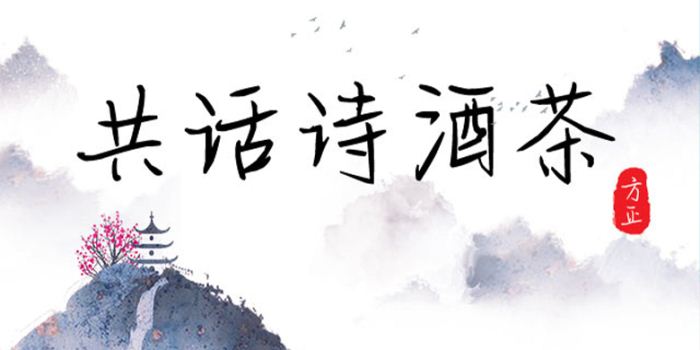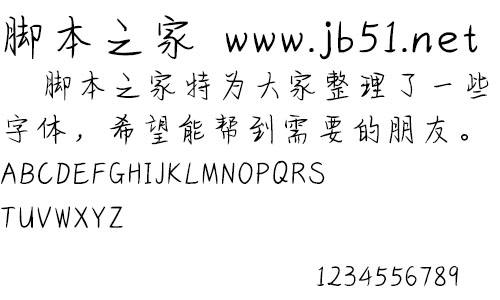
方正手跡-共話詩(shī)酒茶由方正字庫(kù)劉殿儒設(shè)計(jì)師出品的藝術(shù)字體,該字字形中宮緊收,主筆適當(dāng)伸長(zhǎng),獨(dú)具韻味,適合應(yīng)用于藝術(shù)設(shè)計(jì)、平面宣傳設(shè)計(jì)、網(wǎng)頁(yè)設(shè)計(jì),書法等領(lǐng)域。
共話詩(shī)酒茶這款字體筆法豐富,有很多傳統(tǒng)書法的影子。字形中宮緊收,主筆適當(dāng)伸長(zhǎng),獨(dú)具韻味。適用于文藝類的書刊、品牌廣告和產(chǎn)品包裝設(shè)計(jì),以及社交網(wǎng)絡(luò)的個(gè)性化用字。。。